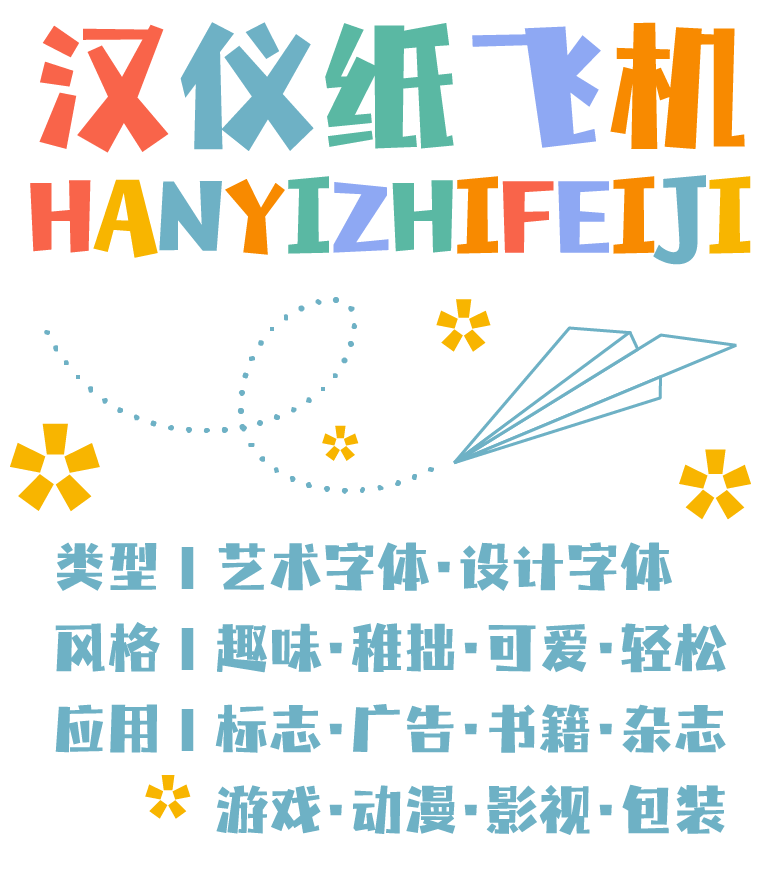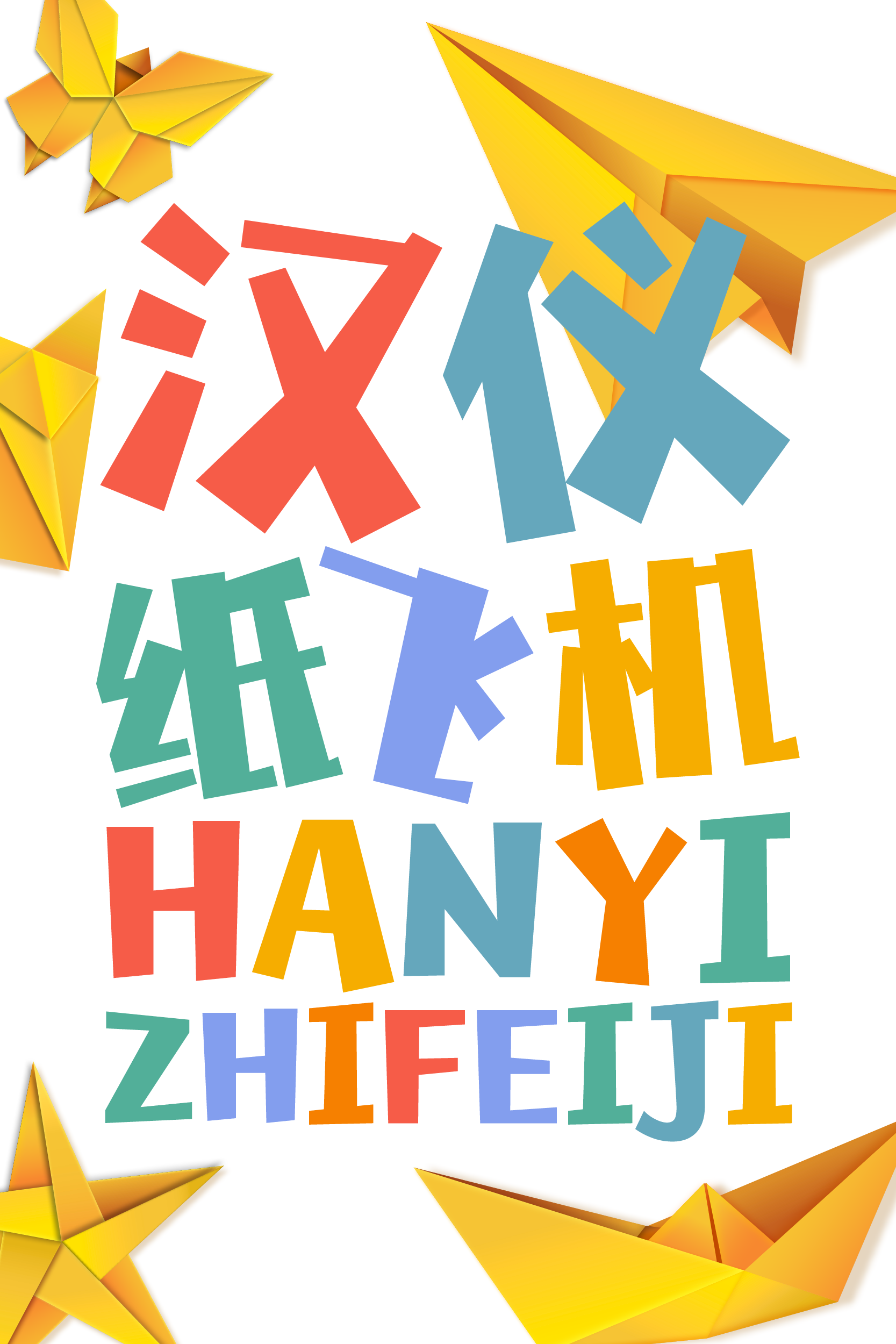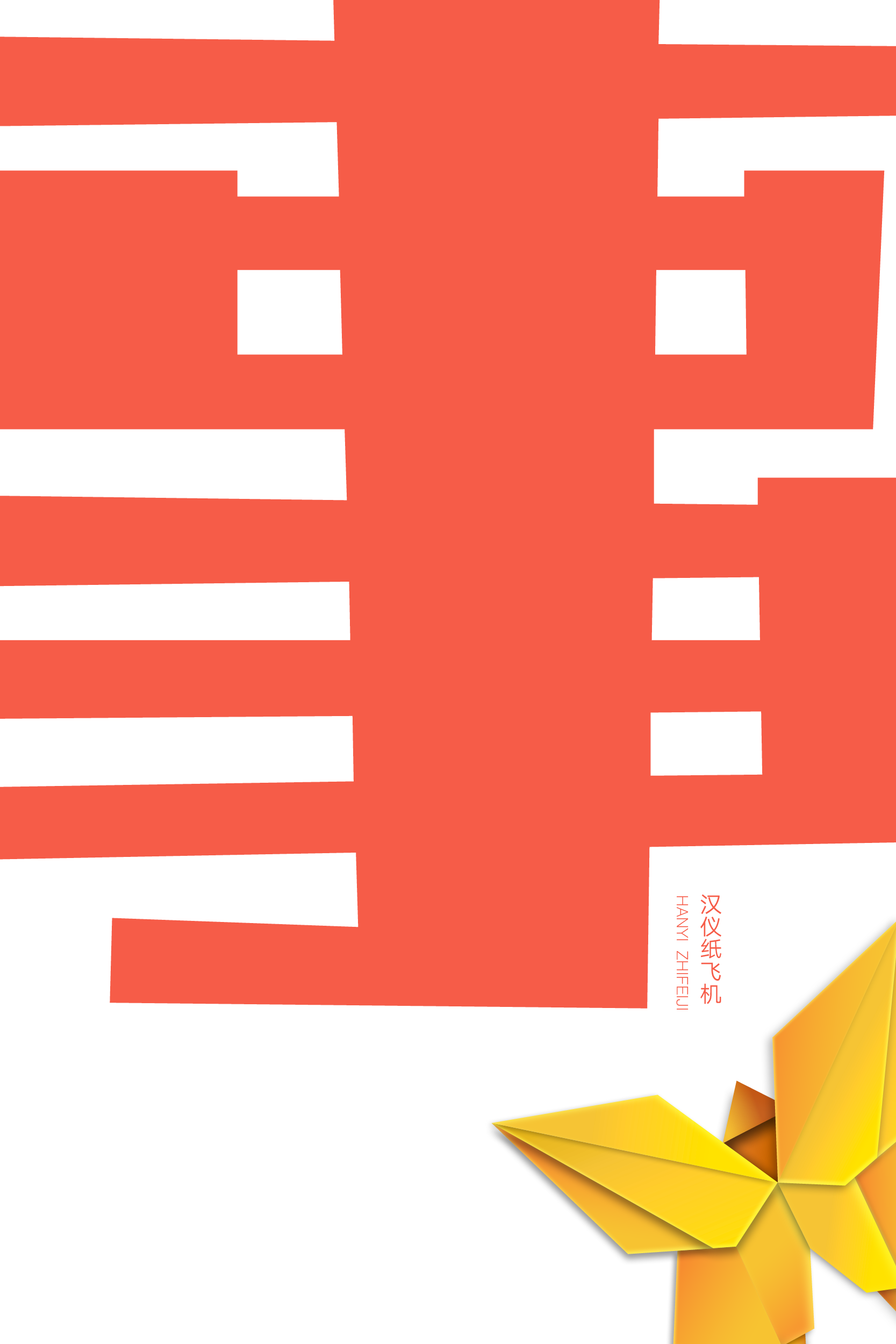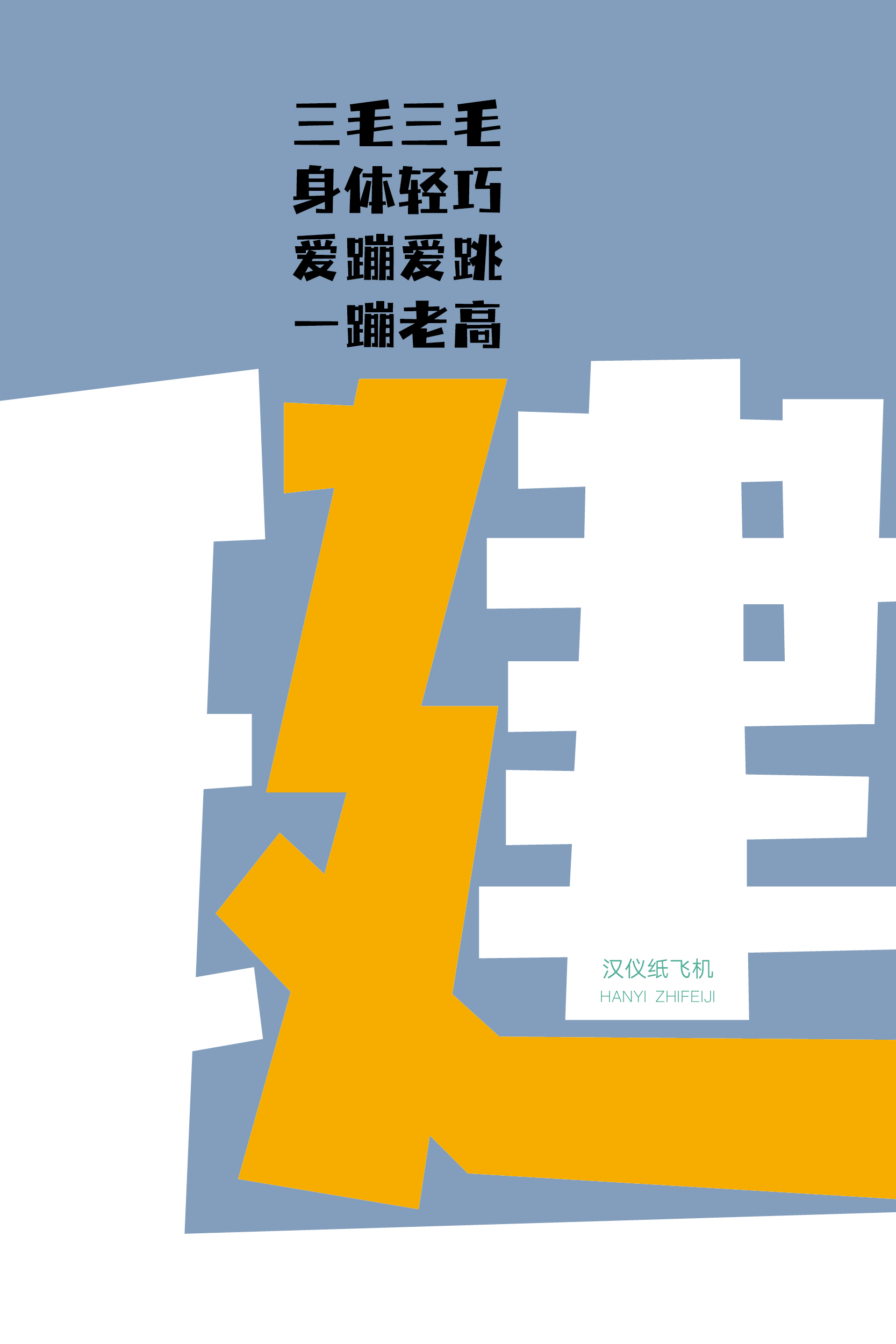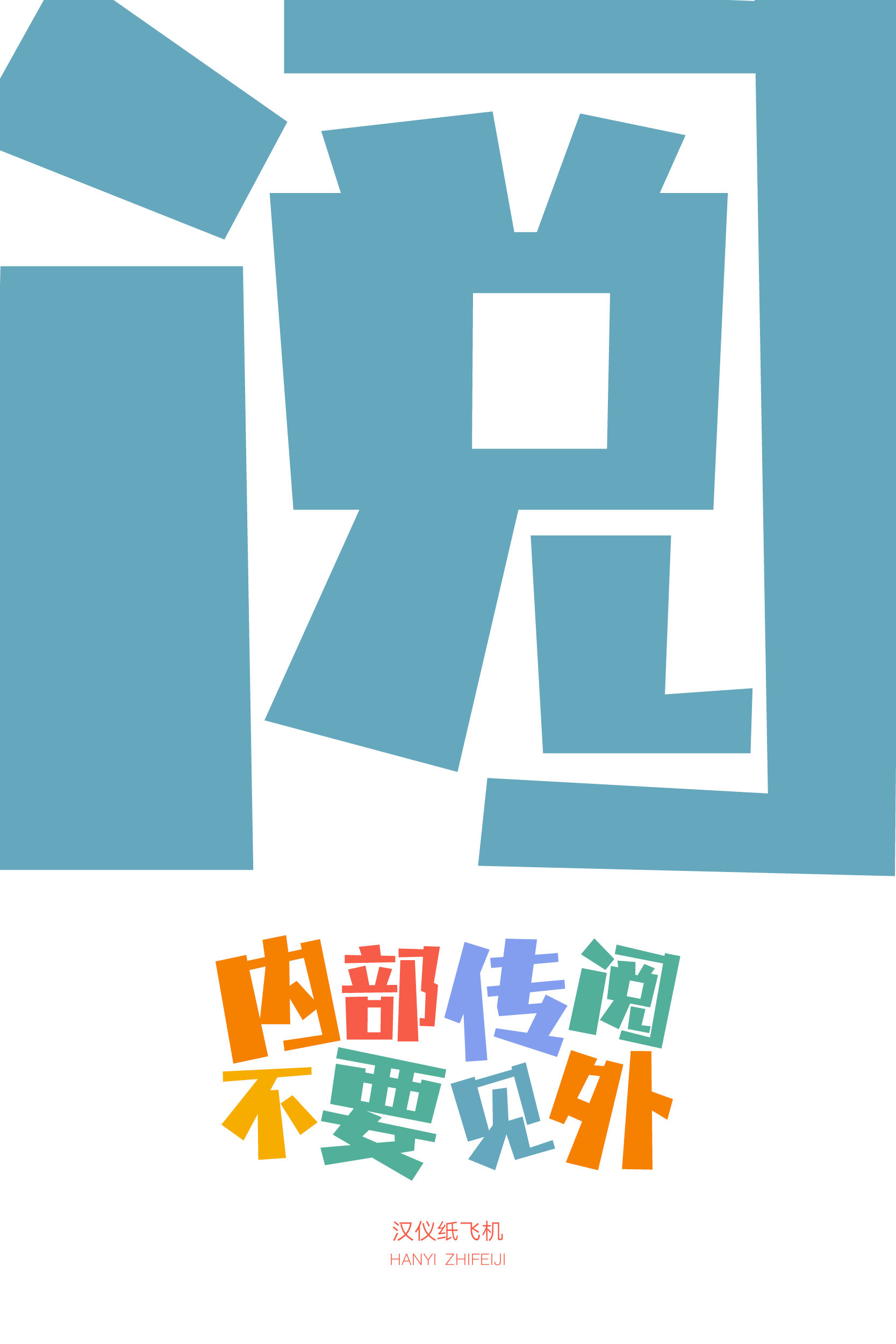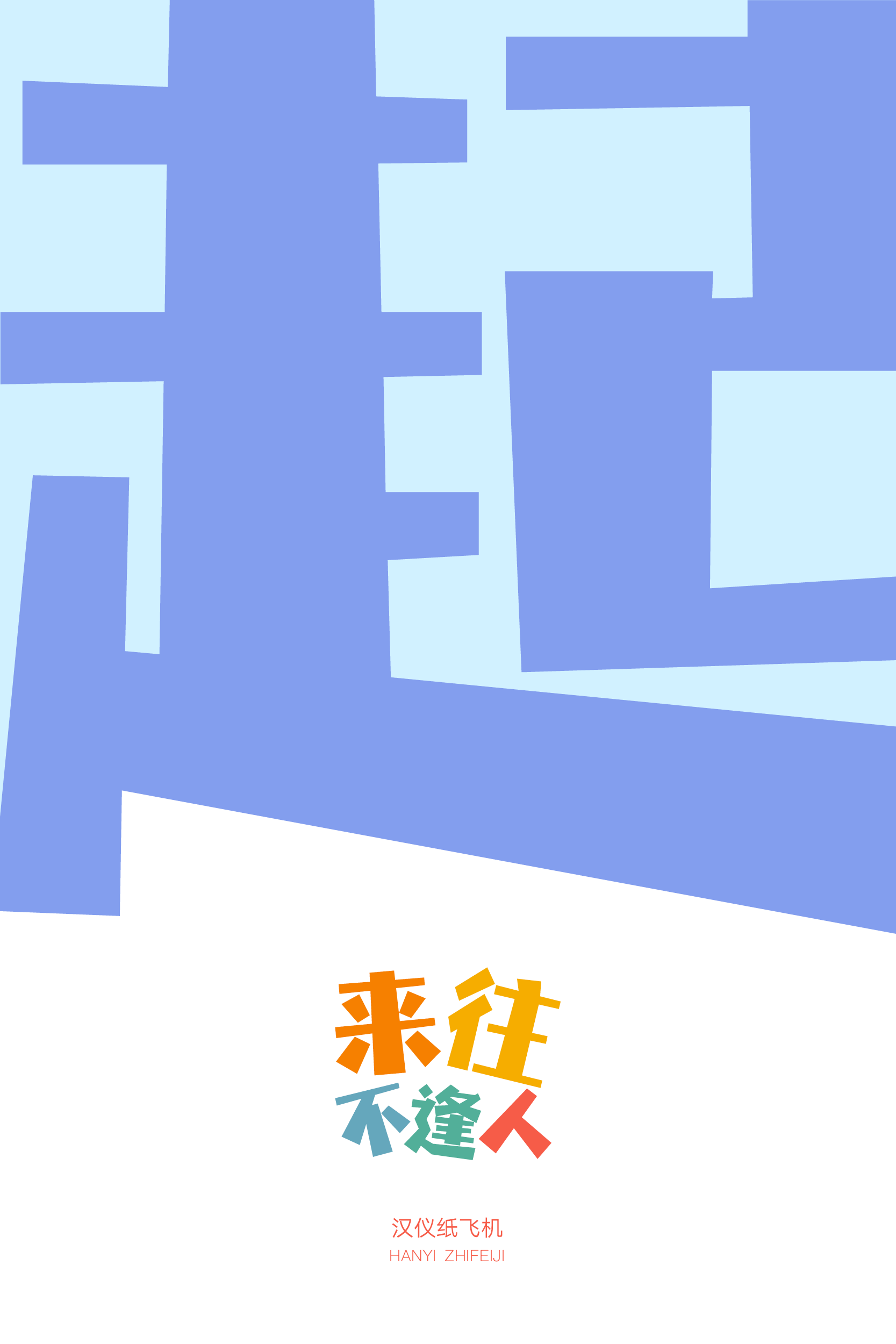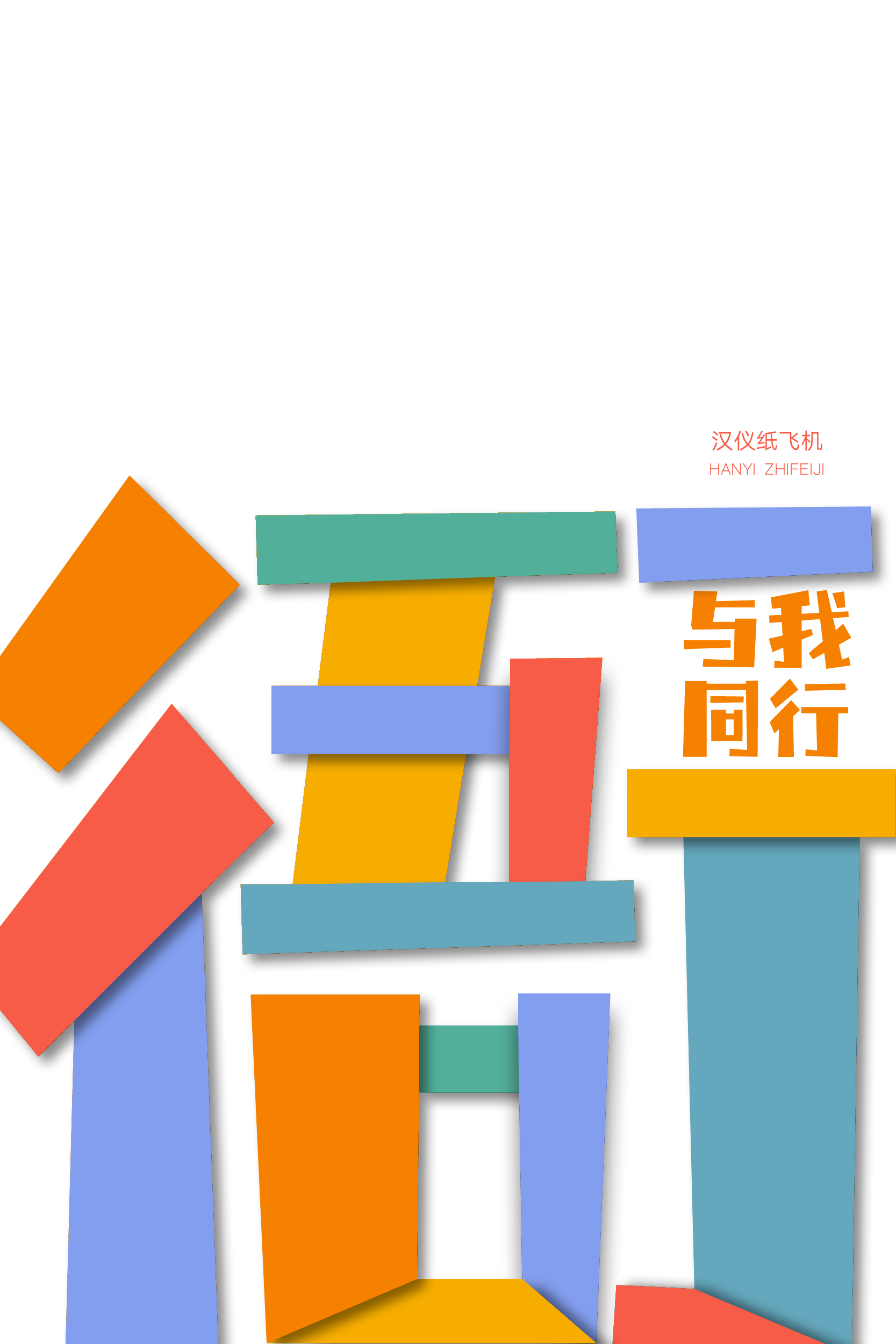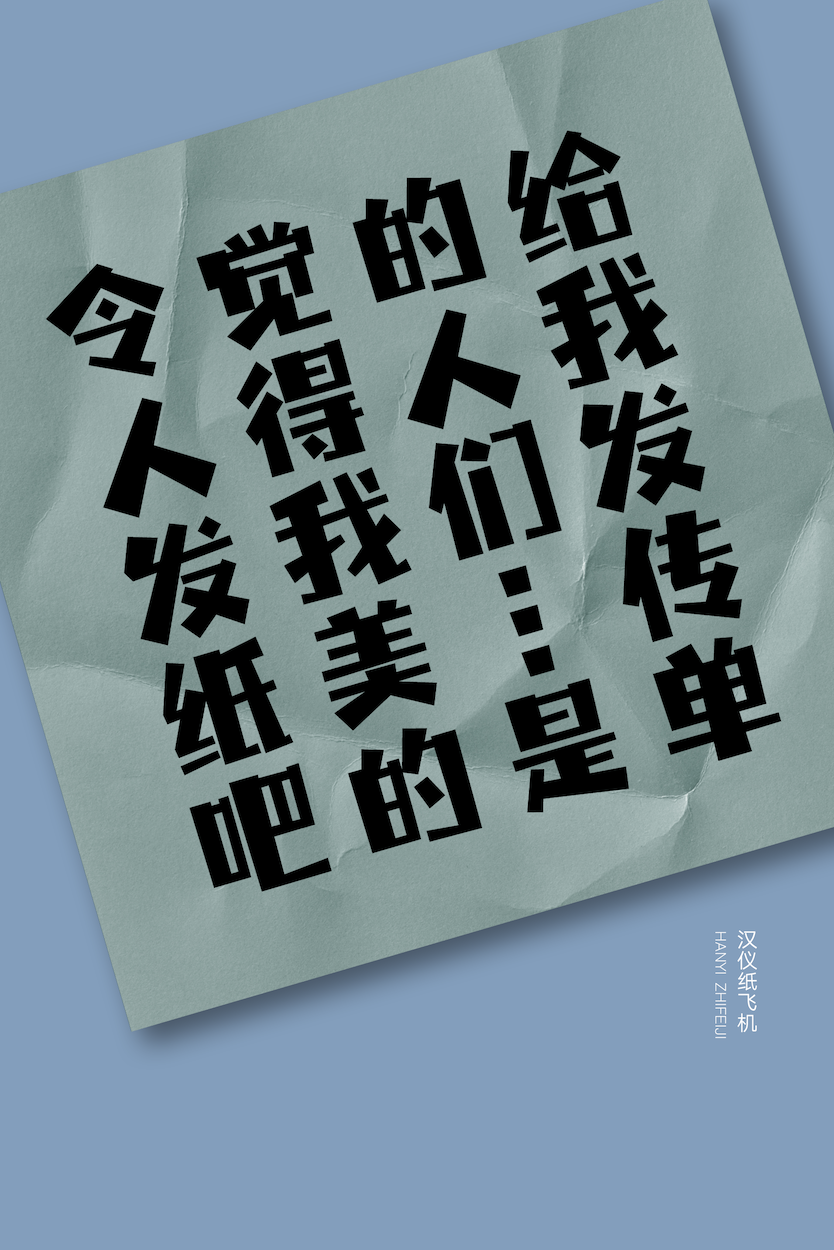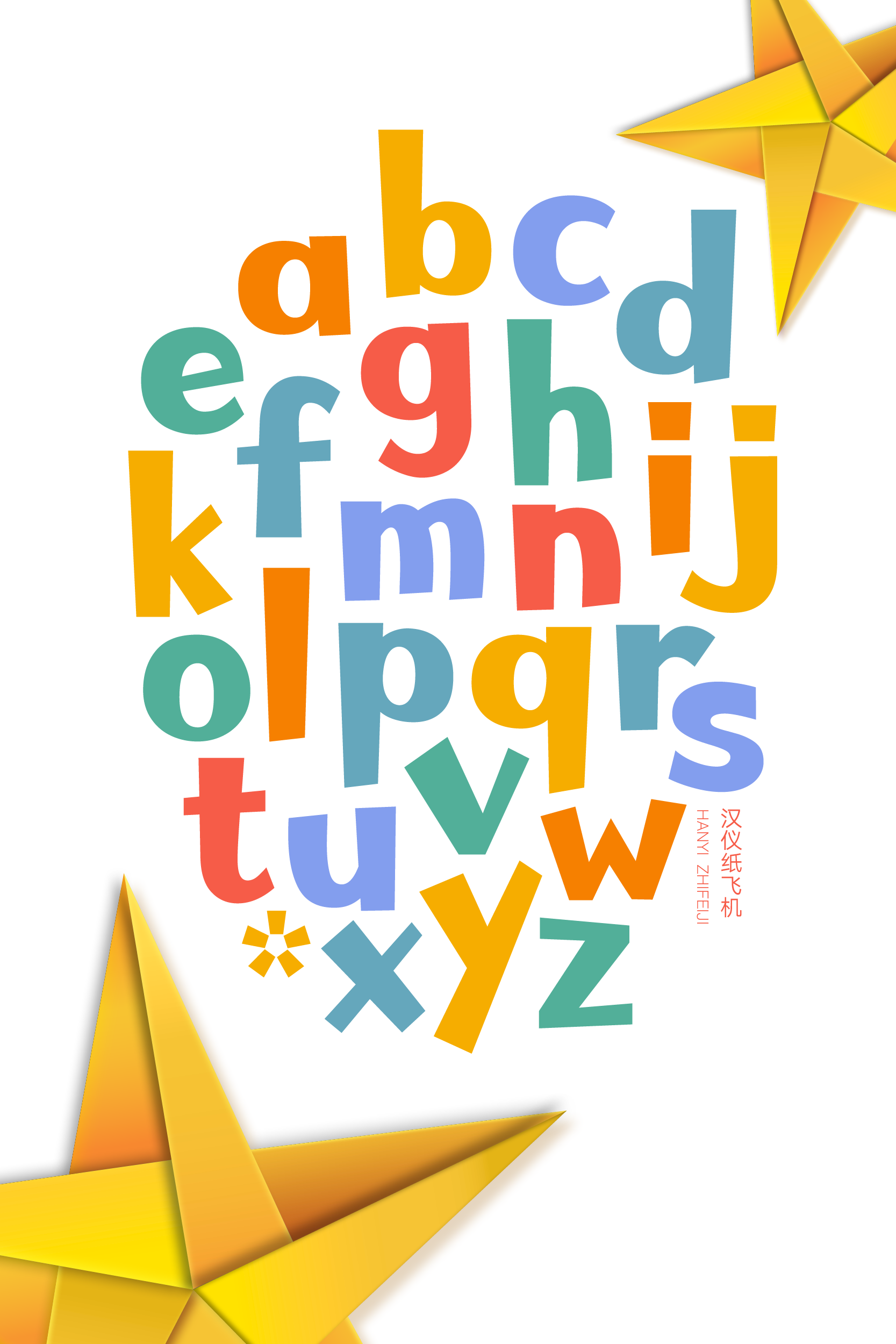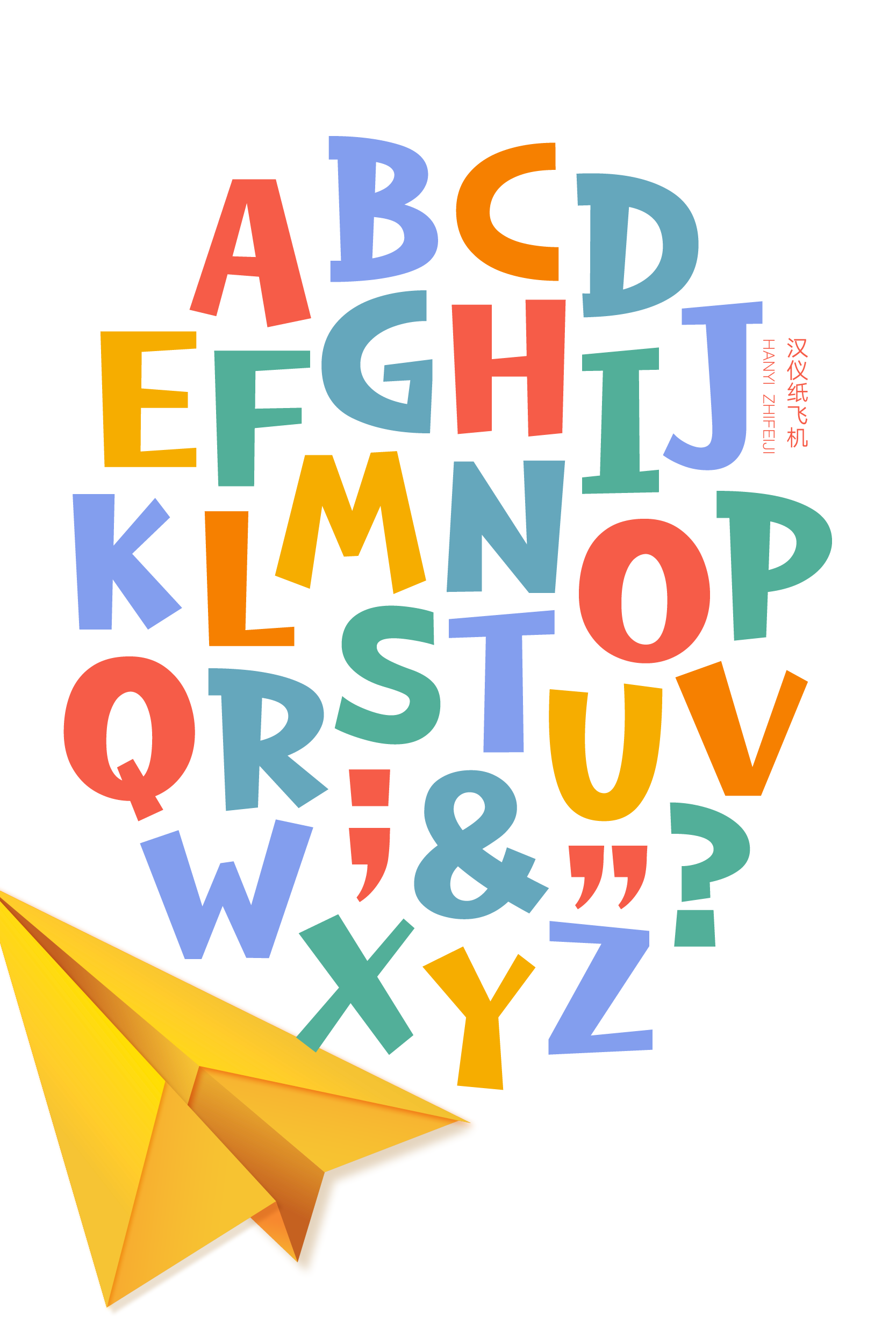
令人怀念起童年的艺术字体
汉仪纸飞机是一款充满稚拙趣味的艺术设计字体,粗细变化丰富的直线笔画看起来就像是纸张折痕,活泼的字形和笔画倾斜度令人怀念起童年记忆中自由自在的纸飞机。这款字体带有手工感和装饰性,适合用于标题排版和较短文本的排版,在儿童绘本、少儿读物、学生文具、玩具周边等使用场景中为版面注入活力。
方直的字形重心平稳,如同纸张一样层叠错落,稚拙可爱。
直线笔画富有粗细变化,变弧线为折痕,具有折纸手工感。
自由随性的倾斜度增添了俏皮活泼的装饰感。
汉仪纸飞机的西文部分由汉仪字库字体设计师李田宇创作,保留了折纸手工感和装饰感,中西文搭配使用有着双倍的轻松趣味。
汉仪纸飞机适合用于标题排版和较短文本的排版,在儿童绘本、少儿读物、学生文具、玩具周边等使用场景中为版面注入活力。